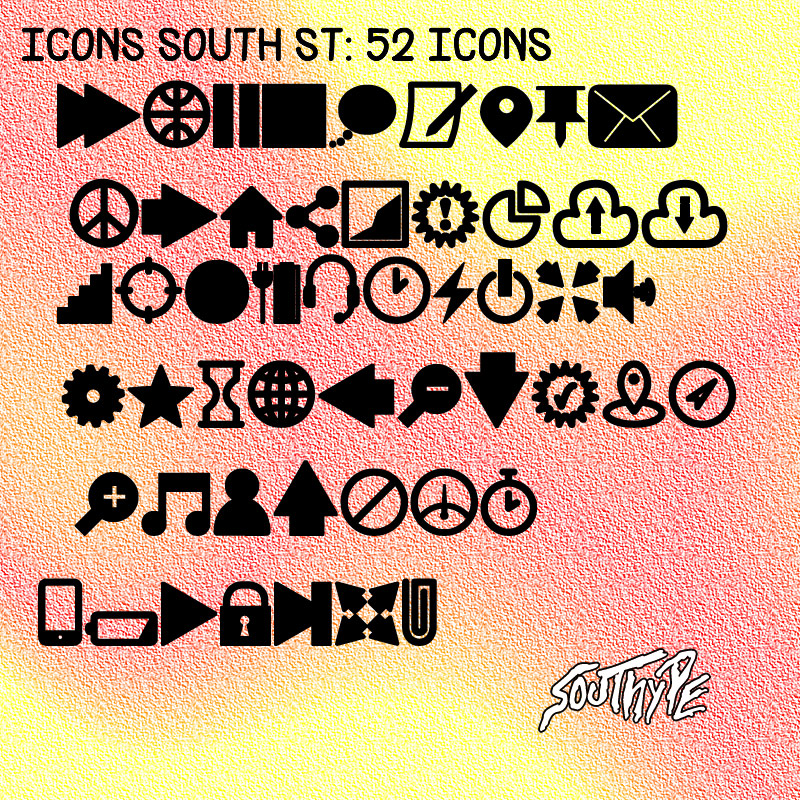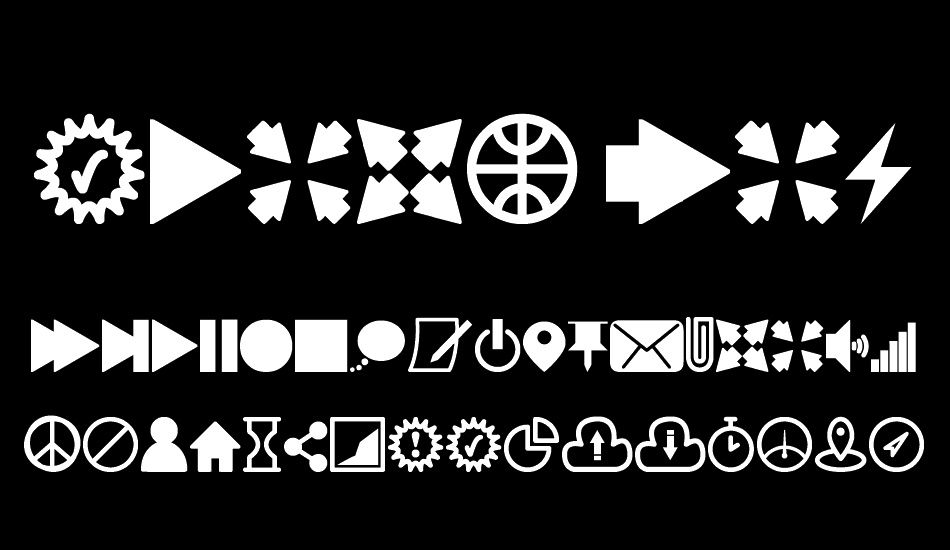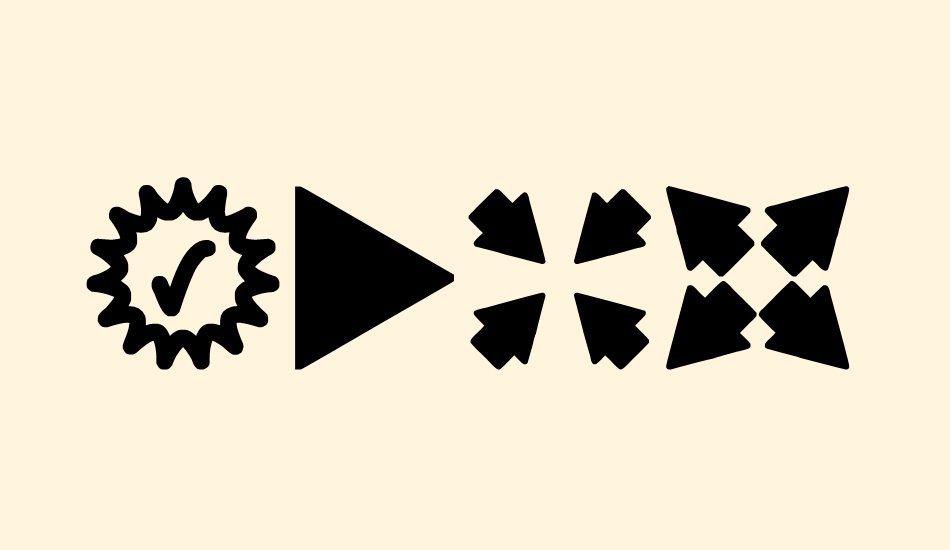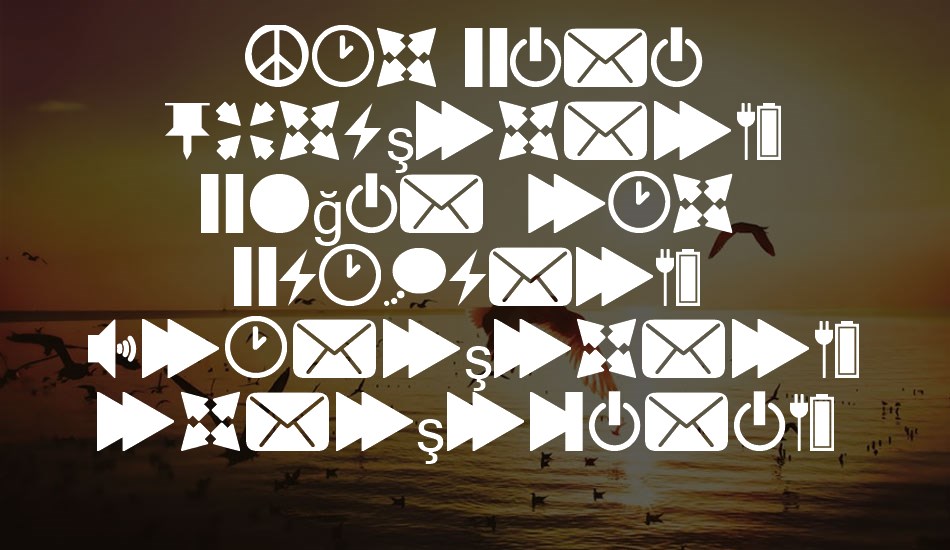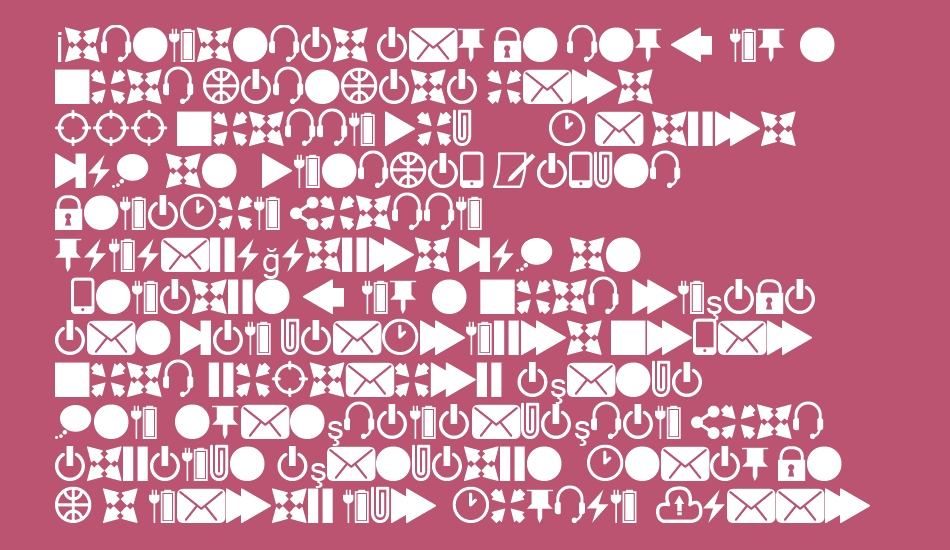
Harita yer simgeleri, Ana Sayfa ikonu, başlat dur butonu, bilgi balonu, not defteri, mektup mail simgesi, cep telefonu simgesi, sarj simgesi, müzik simgesi, büyüt küçült simgesi, zoom in zoom out icon, aç kapa butonu, bozulmadan vekteröl büyütme ve kolay kullanım sınırsız renk seçeneği font.
Icons South St font